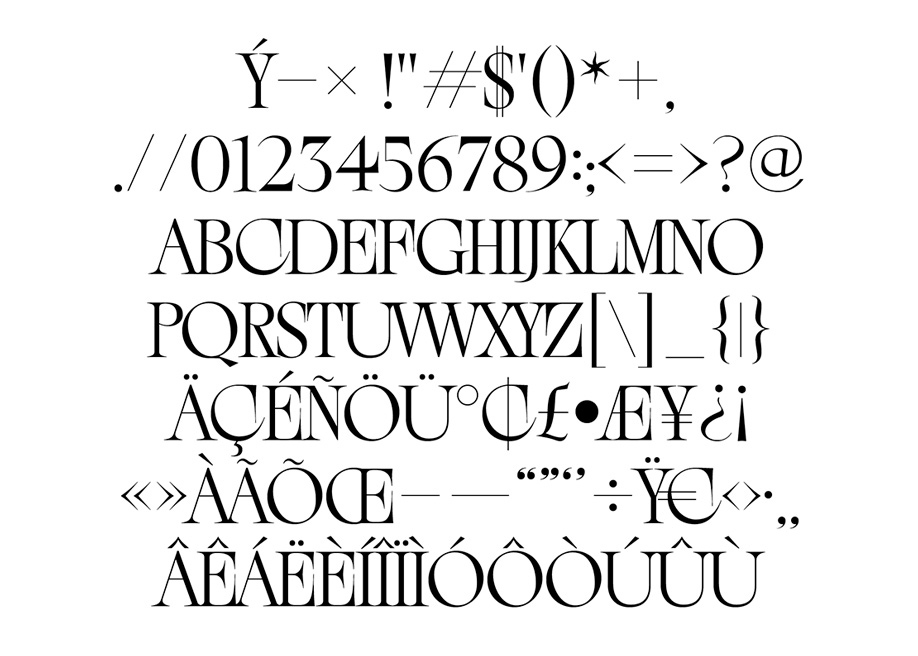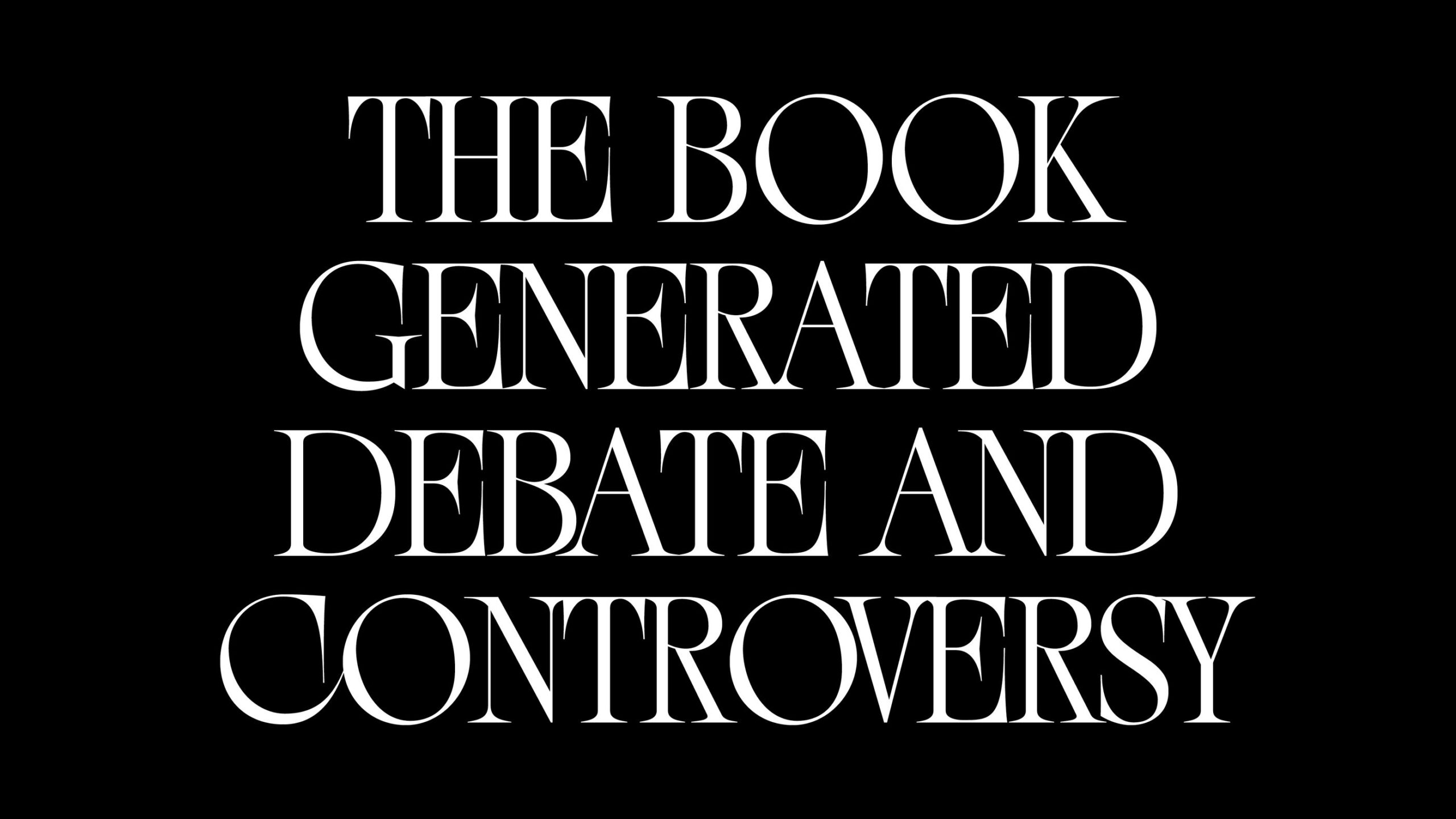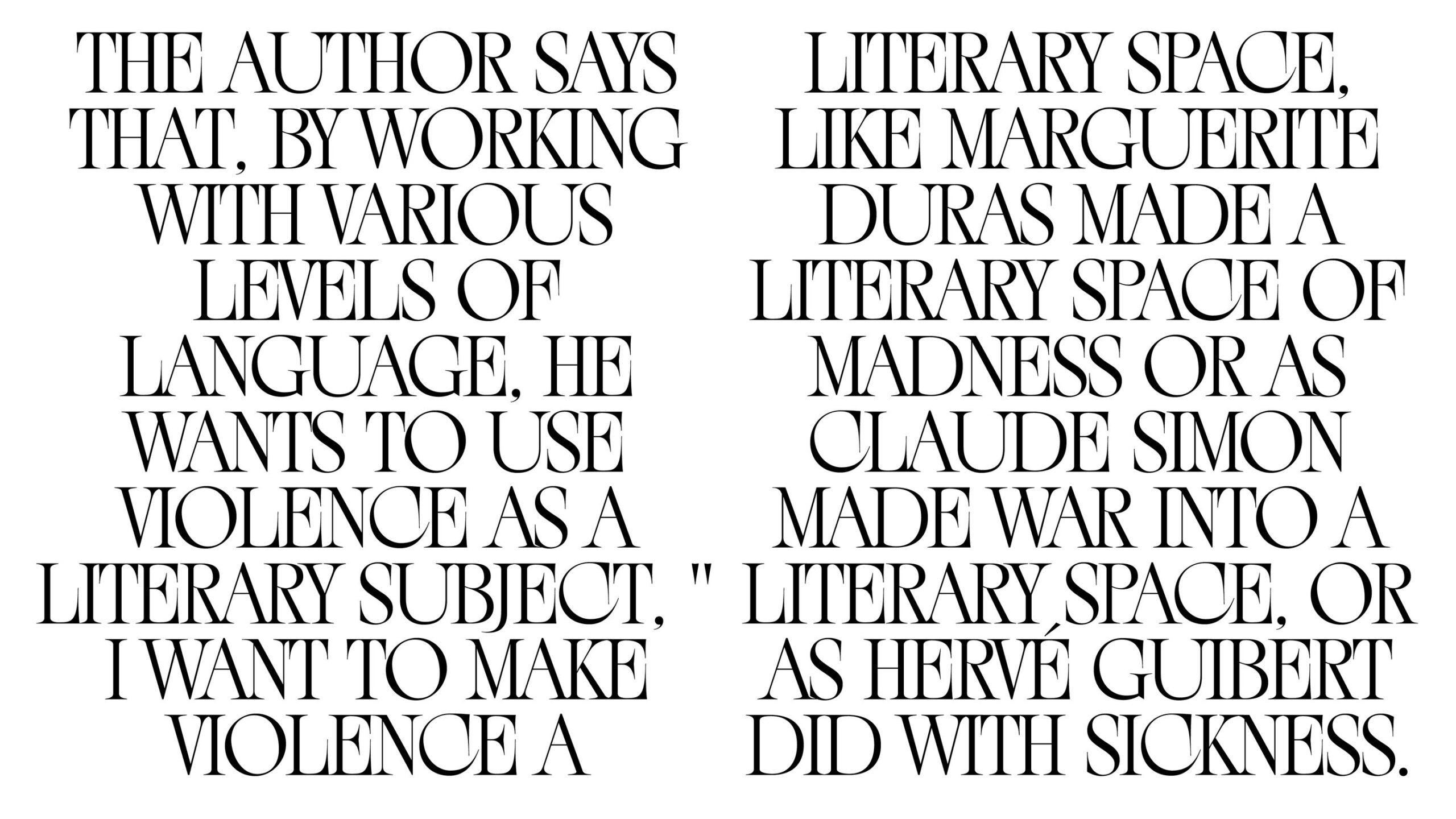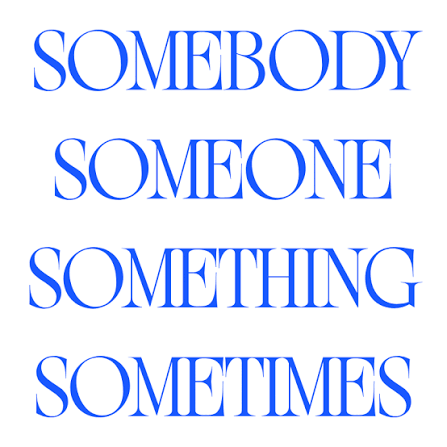
New Eddy Font là bộ phông chữ thuộc dòng Display hiện đại mang phong cách trẻ trung, thân thiện và tràn đầy sức sống mới mẻ. Với sự kết hợp khéo léo giữa cấu trúc hình học tối giản và những đường nét bo góc nhẹ nhàng, phông chữ này mang lại diện mạo ấm áp, gần gũi, cực kỳ thích hợp cho các thiết kế bao bì thực phẩm sạch, tiệm bánh thủ công, cà phê hạt và các sản phẩm đời sống tiện ích. Doozypack.vn cung cấp link tải font New Eddy Việt hóa chuẩn kỹ thuật, giúp bạn sở hữu phông chữ thời thượng mà không lo gặp bất kỳ lỗi hiển thị dấu thanh nào khi thiết kế in ấn.
Đặc điểm thẩm mỹ độc đáo của New Eddy Font
New Eddy không đi theo sự sắc nhọn cứng nhắc của các phông chữ kỹ thuật; nó mở ra một không gian thị giác hài hòa, kết hợp giữa tính ứng dụng cao và cảm xúc chân thành.
Phong cách hiện đại mang hơi thở thân thiện và ấm áp
Đặc trưng lớn nhất của New Eddy Font là cấu trúc chữ mở rộng với các đường nét có độ dày đồng đều, các điểm giao nét được xử lý mềm mại tạo cảm giác dễ mến ngay từ cái nhìn đầu tiên. Phông chữ loại bỏ hoàn toàn sự kiểu cách rườm rà, tập trung vào việc mang lại cảm giác minh bạch, đáng tin cậy. Khi đặt New Eddy làm tiêu đề trên bao bì, thương hiệu của bạn sẽ toát lên vẻ ngoài tươi mới, hiện đại và tạo dựng được thiện cảm vững chắc với người tiêu dùng trẻ tuổi.
Cấu trúc chữ rõ ràng với độ dễ đọc tuyệt vời
Các ký tự của New Eddy Font Việt hóa sở hữu tỷ lệ x-height thoáng đãng cùng khoảng hở trong chữ (counter) rộng rãi. Nhờ đó, phông chữ này duy trì được độ sắc nét và khả năng đọc hiểu xuất sắc ở cả kích thước tiêu đề lớn trên nắp hộp giấy lẫn kích thước nhỏ trên tem nhãn dán chai lọ, giúp người xem tiếp nhận thông điệp một cách tự nhiên và thoải mái.
- Hộp giấy bánh ngọt & Tiệm bánh (Bakery): Nét chữ ấm áp gợi cảm giác thơm ngon, rất hợp làm tiêu đề chính trên hộp bánh cookie, túi đựng bánh mì hoặc hộp bánh ngọt gia đình.
- Bao bì thực phẩm hữu cơ & Nông sản sạch: Tiêu đề thương hiệu in bằng font New Eddy kết hợp cùng chất liệu giấy Kraft nâu tạo nên phong cách mộc mạc, lành tính và an toàn sức khỏe.
- Túi giấy thời trang & Quà lưu niệm: Tên cửa hàng in trên túi giấy Ivory cán màng mờ tạo phong cách hiện đại, trẻ trung và rất có gu thẩm mỹ.